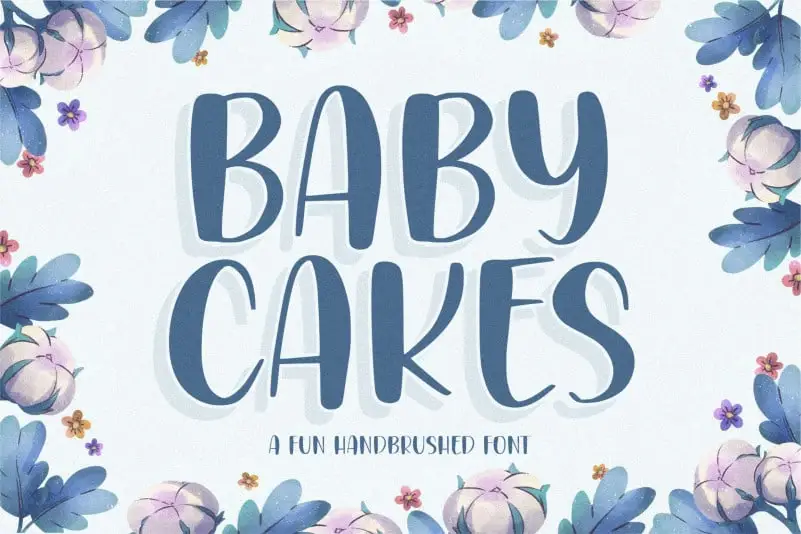
BABYCAKES Handbrushed Font – Fonte Grátis
BABYCAKES Handbrushed Font
A BABYCAKES Handbrushed Font é uma criação única criada por balpirick, ideal para aqueles buscando um toque autêntico e envolvente em seus projetos de design gráfico. Essa fonte artesanal, perfeita para aplicação em embalagens de produto, identidade visual, revistas, mídia social, casamentos ou qualquer outra situação que exija expressar texto acima do fundo, é uma escolha irresistível. Com sua aparência delicada e natural, a fonte BABYCAKES Handbrushed proporciona um toque único e emocionante aos seus projetos. Suas linhas suaves e traços delicados criam um efeito encantador que se assemelha à escrita manuscrita real. É uma excelente opção para aqueles buscando um design mais pessoal ou artesanal, capaz de dar vida ao texto com um toque especial. Esta fonte é perfeita tanto para designers de mídia social quanto para a criação de identidade visual de marcas e produtos que buscam destacar-se em meio aos muitos outros projetos digitais. Com a BABYCAKES Handbrushed Font, você pode criar designs únicos e memoráveis, tornando qualquer projeto ainda mais vívido e autêntico.